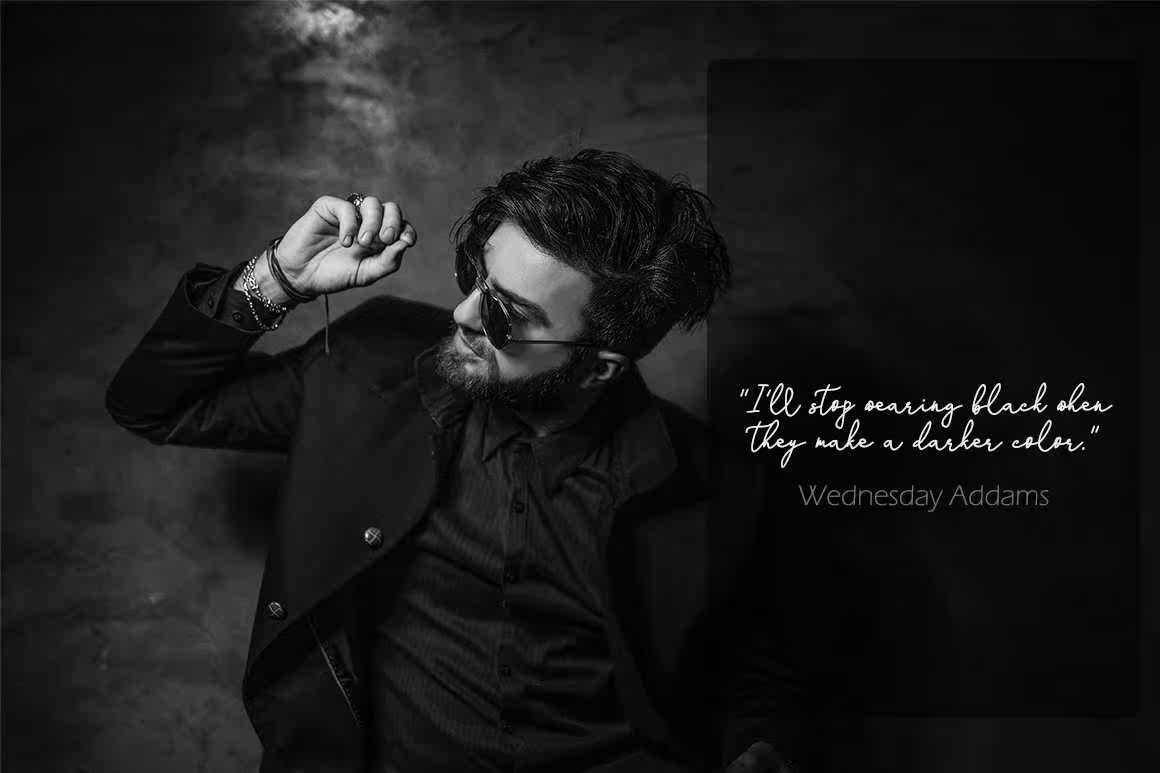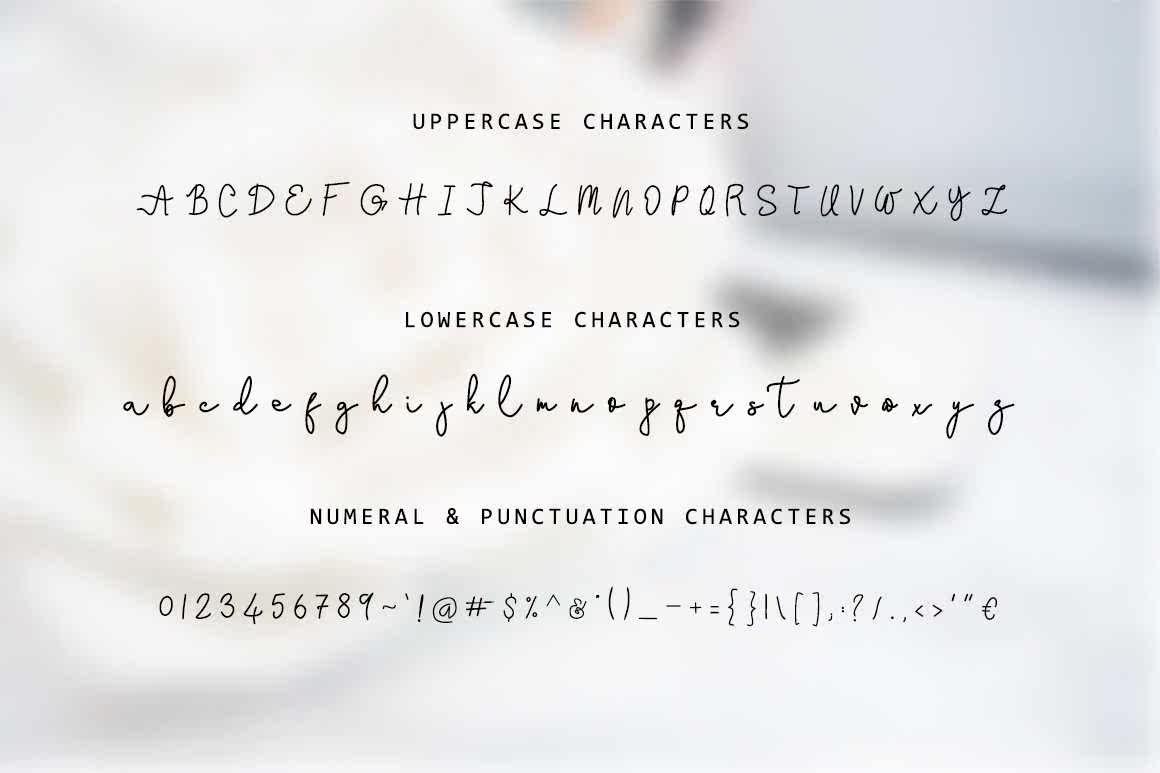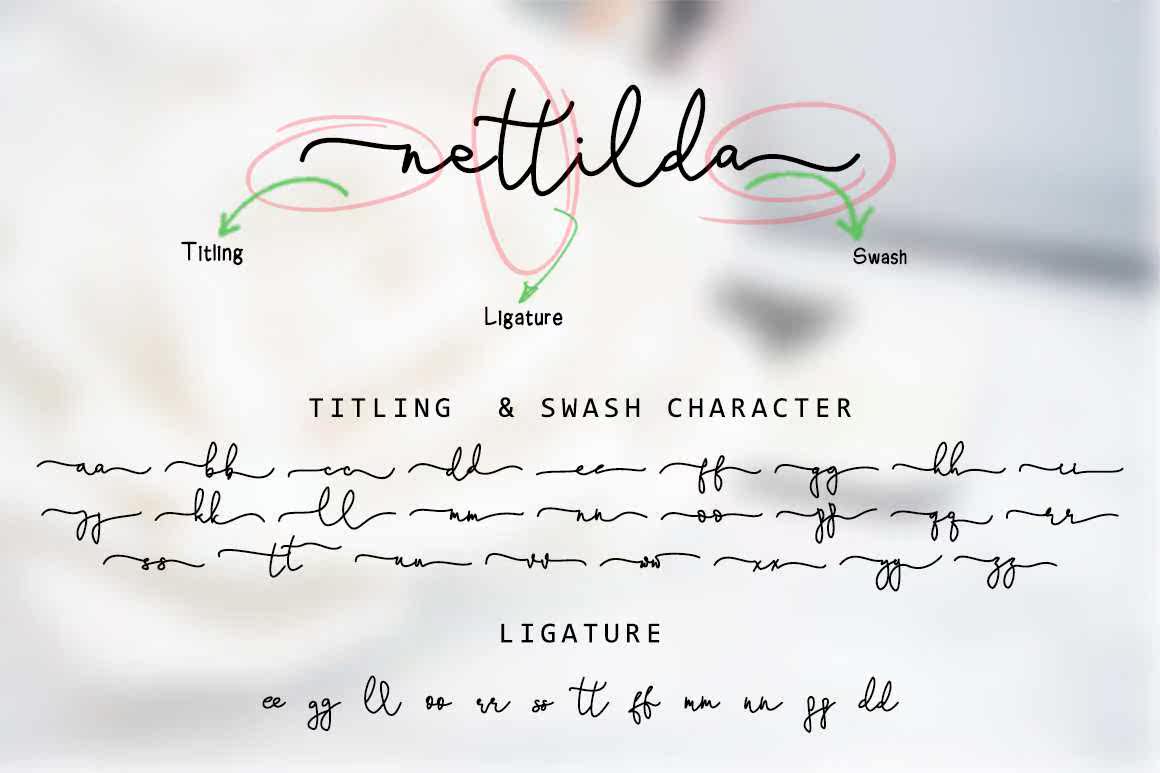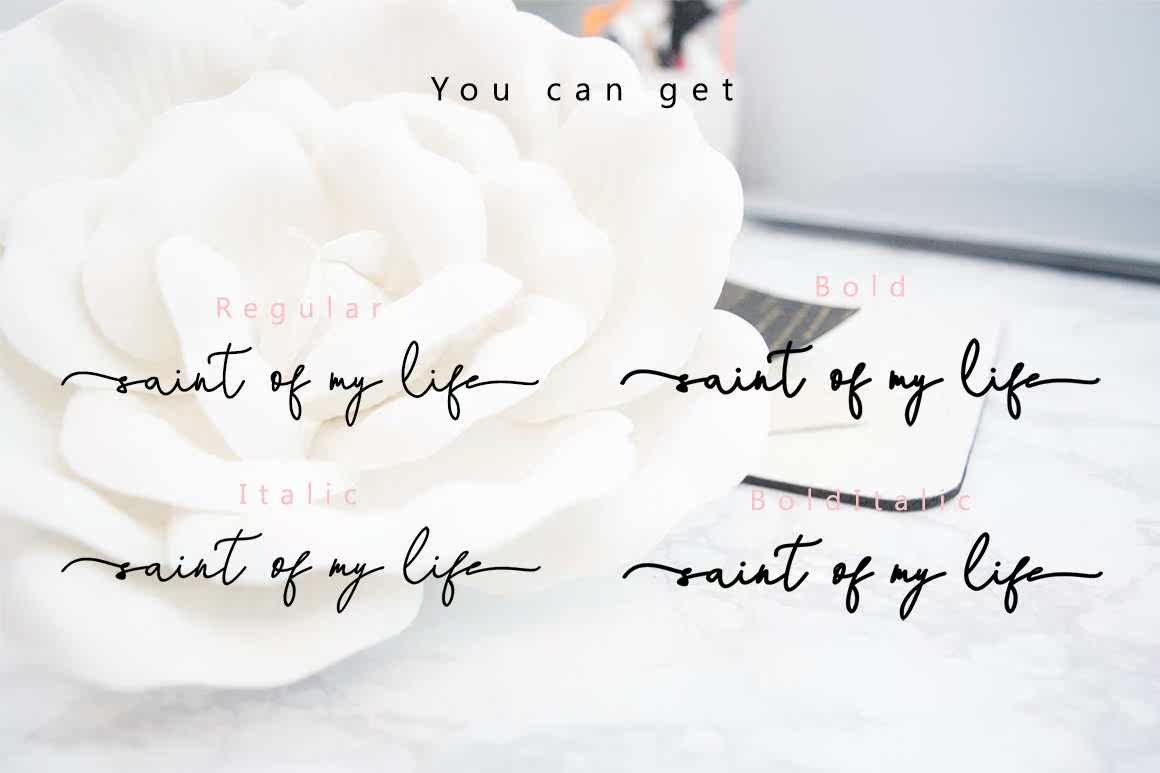
StefaniiSastylishUniqueHandwritenFontandEasyteremember。它主要用于UniqueBranding、photooverlays、水印、名片、请柬、婚礼、摄影、时尚等。StefaniSastylishUniqueHandwritenFontandEasyteremember。它主要用于UniqueBranding、photooverlays、水印、名片、请柬、婚礼、摄影、时尚等。